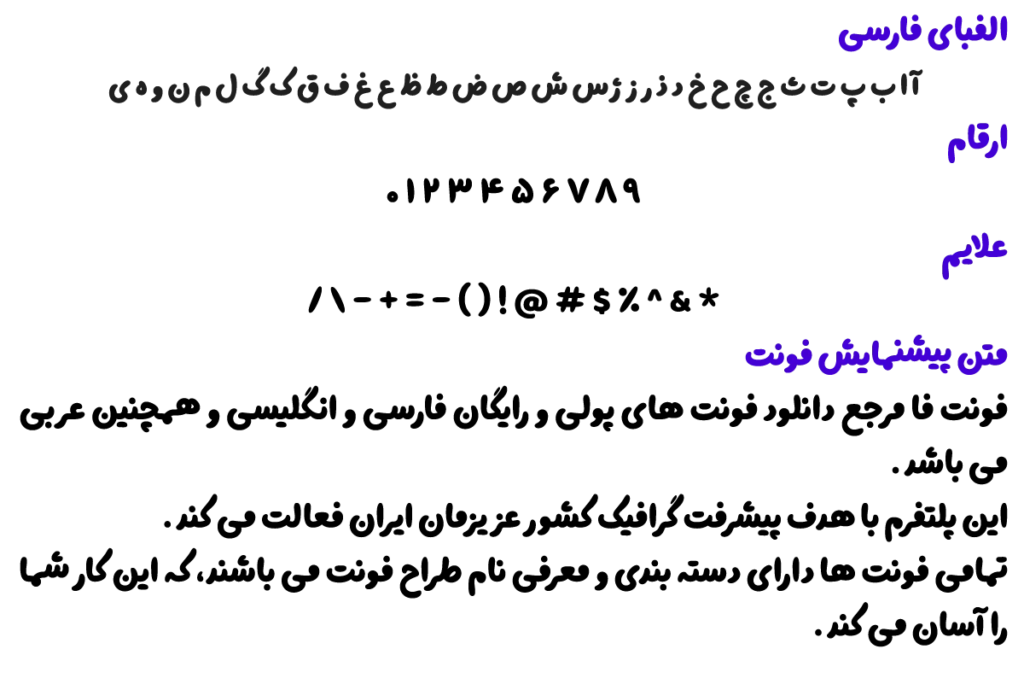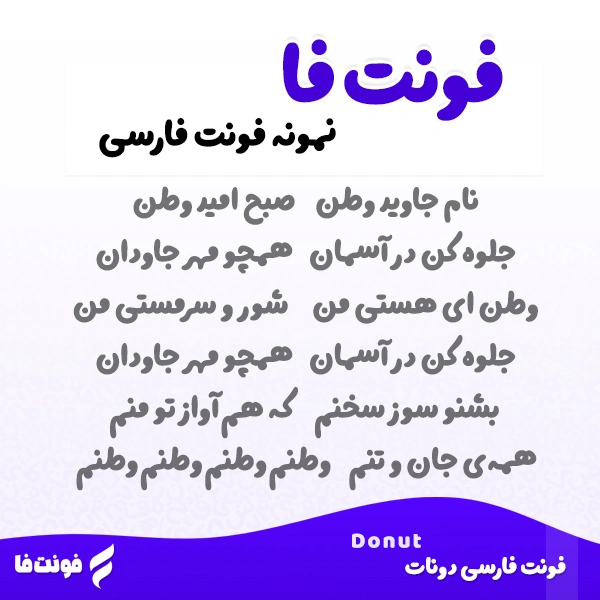
فونت فارسی دونات – Donut
توضیحات و معرفی فونت دونات
فونت فارسی دونات ( Donut ) از مجموعه فونت های آزاد و پولی می باشد، همچنان نوع فونت دست نویس می باشد.
فونت شگفت انگیز و زیبای فوق در سال 1405 طراحی و ساخته شده است.
حروف لاتین دونات، از فونت baloo2 گرفته شده (با اندکی تغییر)
به نقل از طراح فونت
یه نکته جالب! میدونستید دونات رو بر اساس خط خودم طراحی کردم؟ این پایین پروسه طراحی رو از روی کاغذ تا خروجی نهایی ببینید
طراحی دونات رو از سال ۱۴۰۳ شروع کردم. ایده اولیه این بود که دستخط خودم رو که ازش برای تولید عکس نوشته استفاده میکردم و بار ها مورد استقبال دیگران قرار گرفته بود، تبدیل به فونت کنم.
هر کدوم از حروف دونات رو بار ها باز طراحی کردم و و با وسواس زیادی روی جزئیاتشون کار کردم تا به پختگی لازم برسن. چیزی که باعث شده دونات هویت منحصر به فرد و جدیدی داشته باشه.
از دونات زمانی استفاده کنید که میخواین صمیمیت، شادابی، انرزی مثبت و حال خوب رو به مخاطبتون منتقل کنید و باهاش خودمونی حرف بزنید. البته اگه مخاطب نوجوان دارید اصلا از دونات دریغ نکنید چون ارتباط خوبی باهاشون برقرار میکنه 🙂
در تصویر زیر میتوانید شعر دلنشین «نام جاوید وطن» را ببینید که با این تایپ فیس فارسی طراحی شده است.